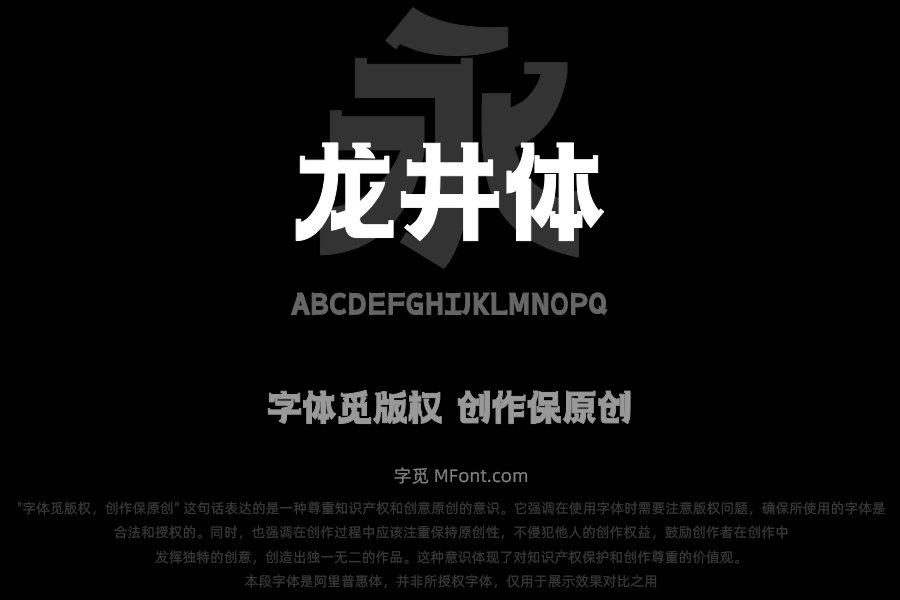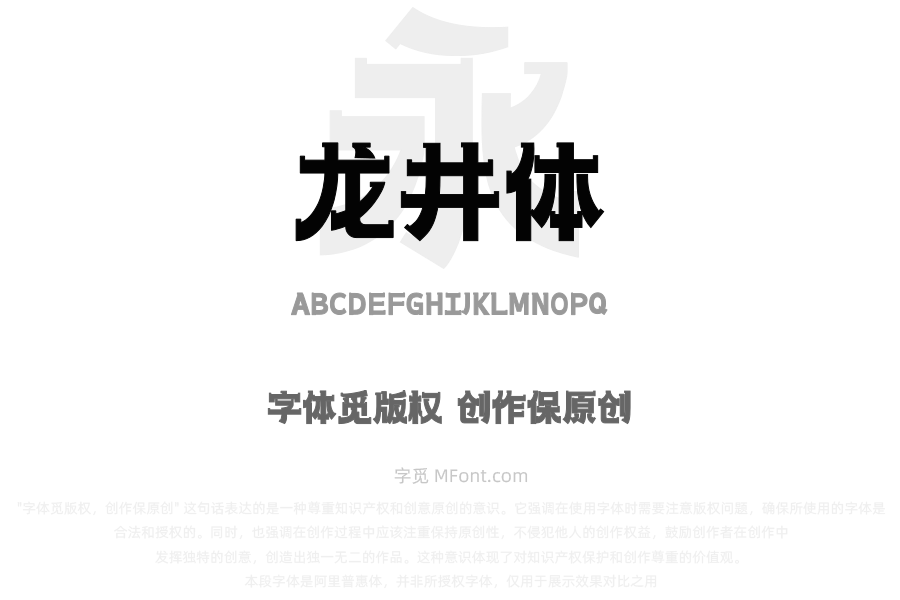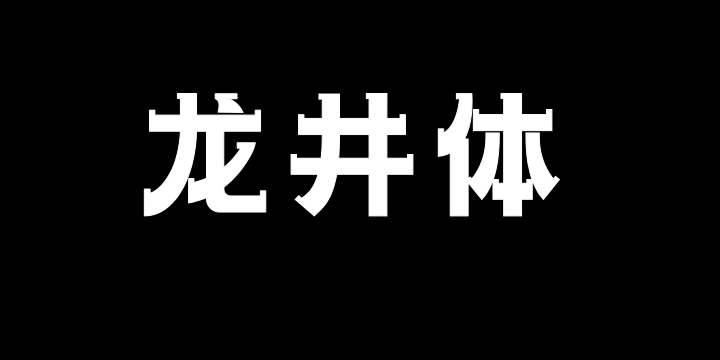
• 上首龙井体
字体全名: 上首龙井体
字体简介: 上首龙井体,简体中文约6763字,这是一款富有创意的字体,融合了现代黑体的特色,风格劲爽简约,推荐用于品牌LOGO、展览标题、文化类出版物封面等领域,其独特的解构形态既能凸显设计主题的先锋性,又能通过汉字本身的文化内涵传递深层价值,实现“形式为内容服务”的设计目标。